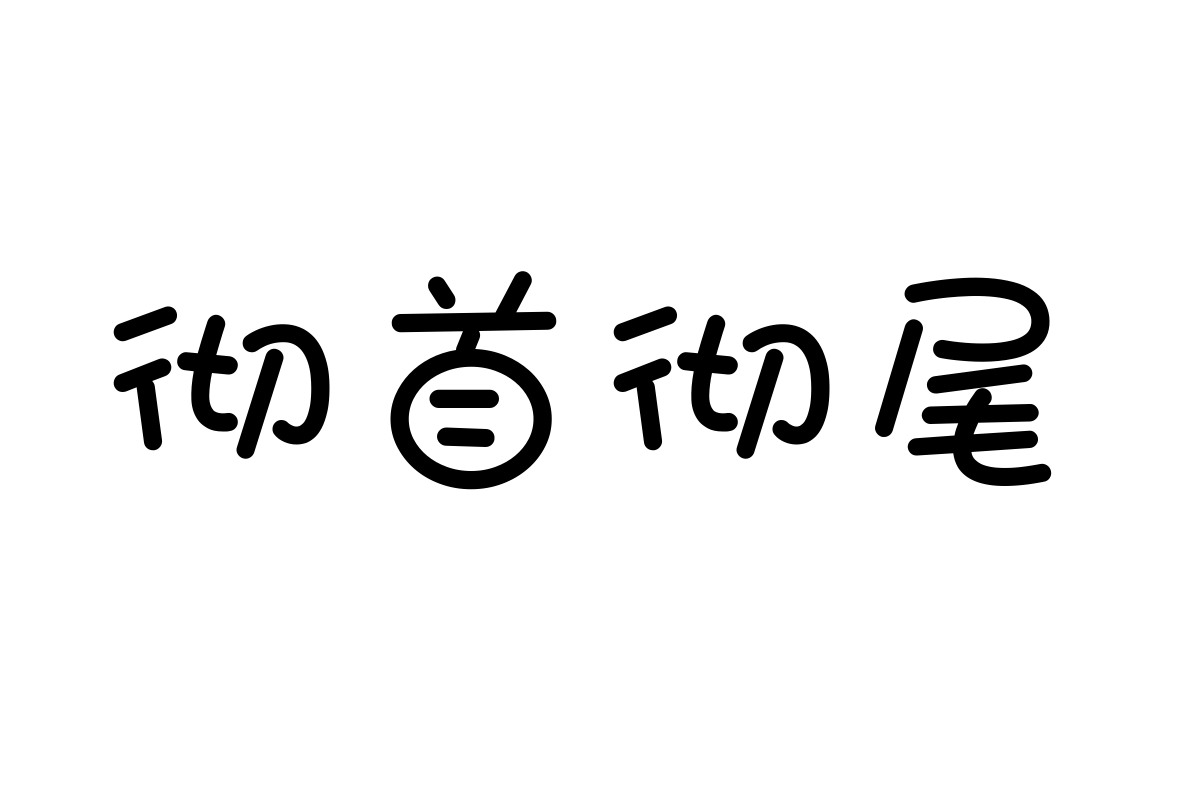
汉仪乐喵体是一款免费开源的中文字体,由汉仪字库公司开发。这款字体以其可爱的卡通形象和流畅的线条设计而受到广泛欢迎。
汉仪乐喵体采用了现代简约的设计风格,笔画圆润饱满,整体给人一种轻松愉快的感觉。它适用于各种需要可爱风格的应用场景,如儿童插画、漫画、广告设计等。同时,这款字体也具有较高的识别度和辨识度,适合用于品牌宣传和产品包装设计。